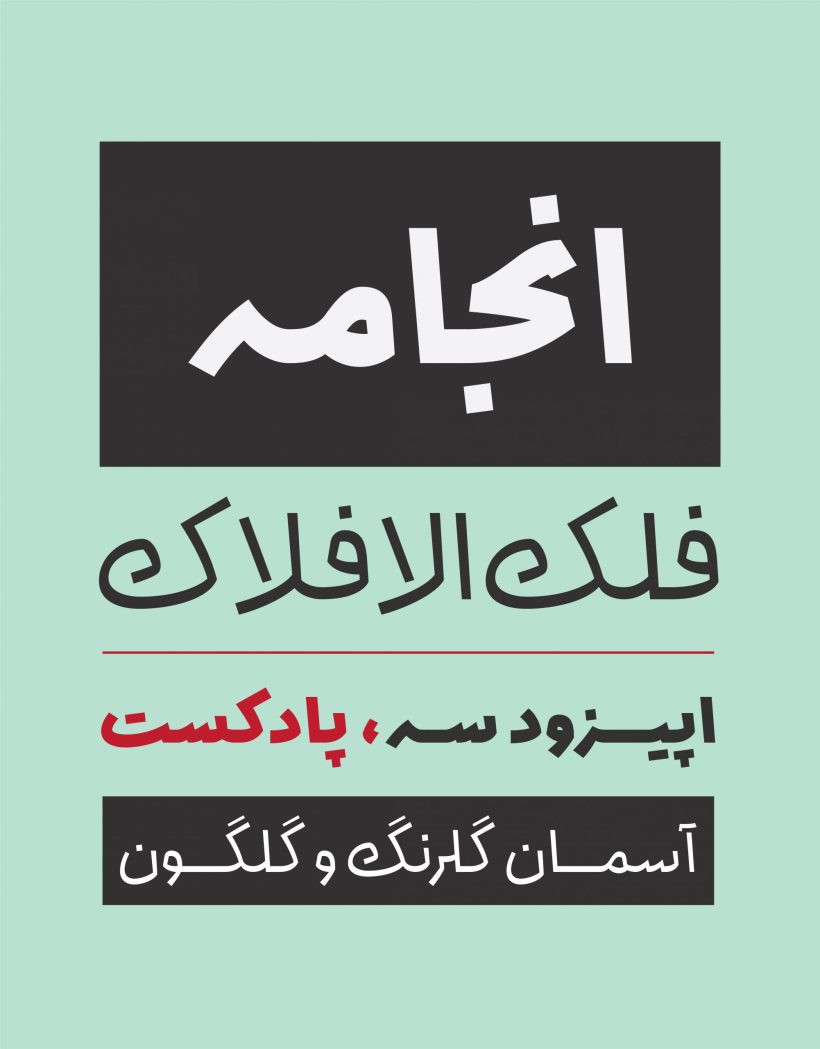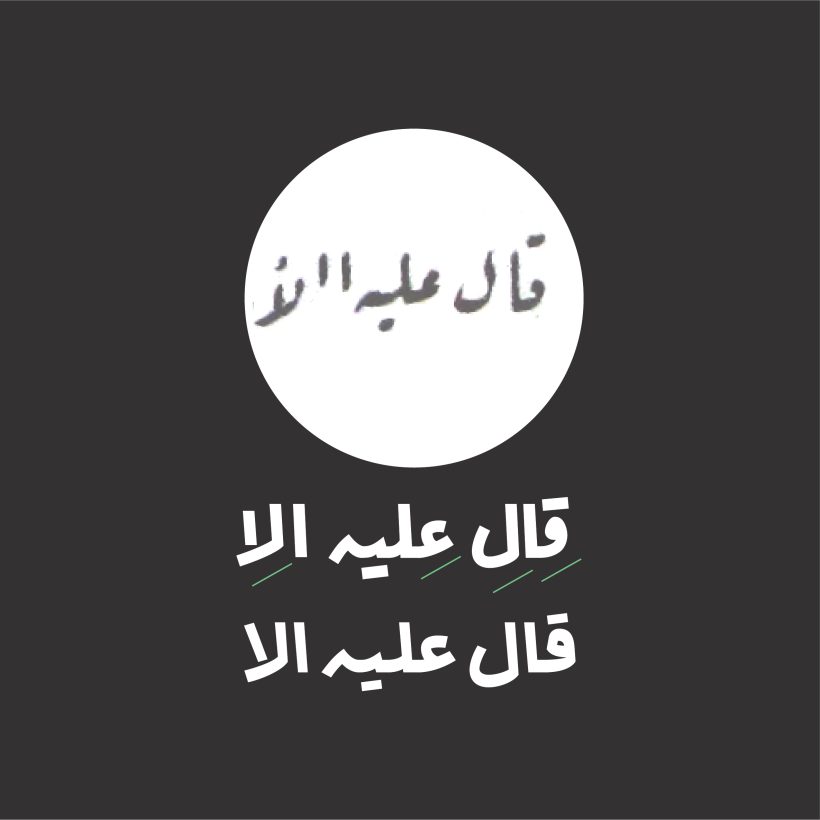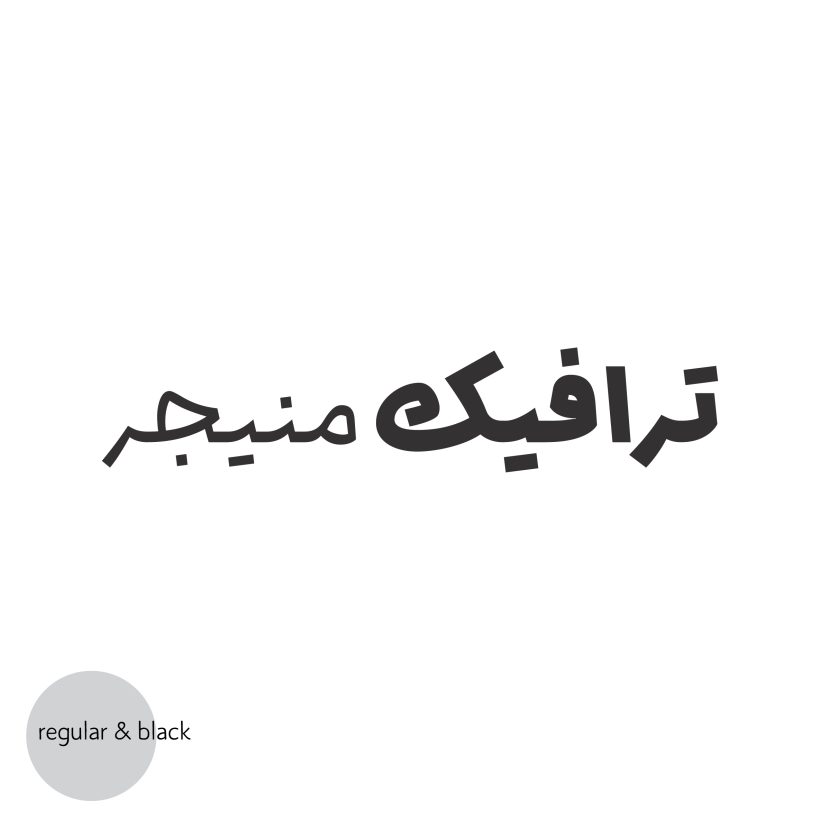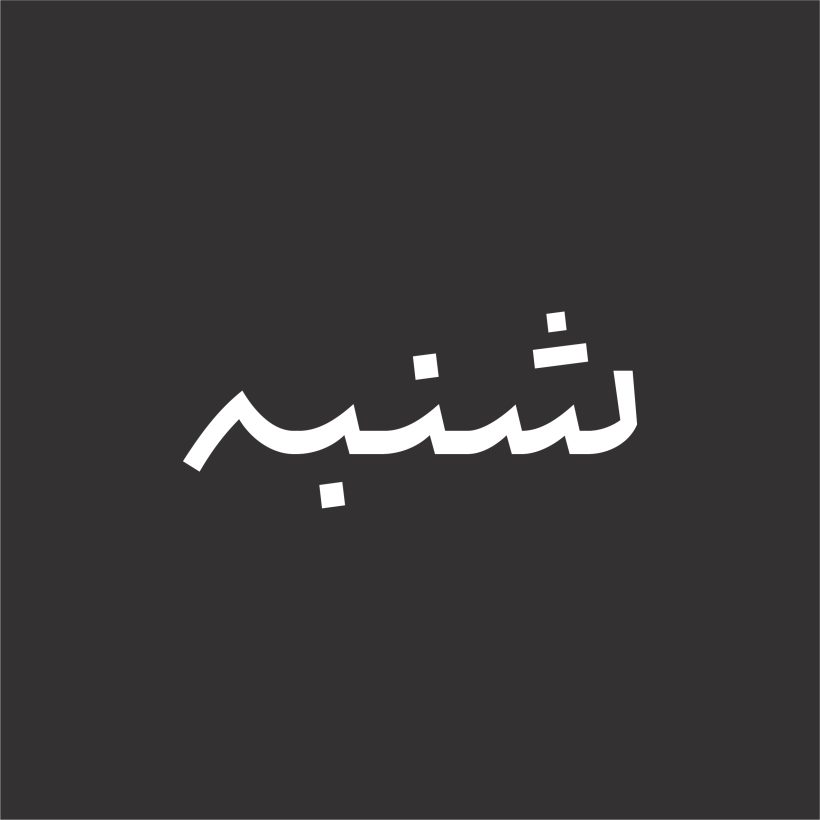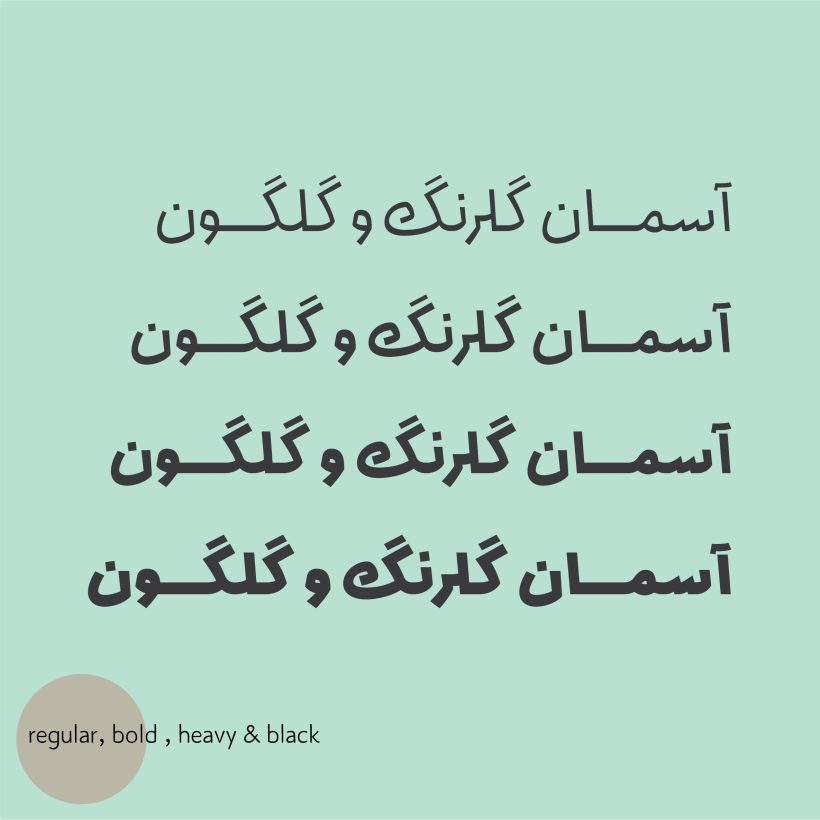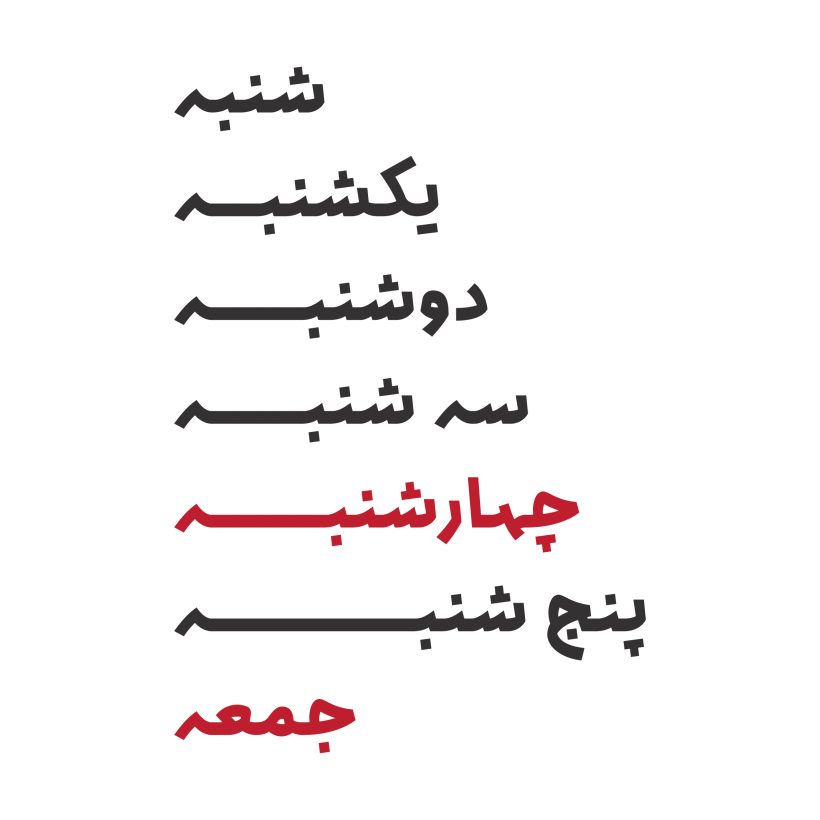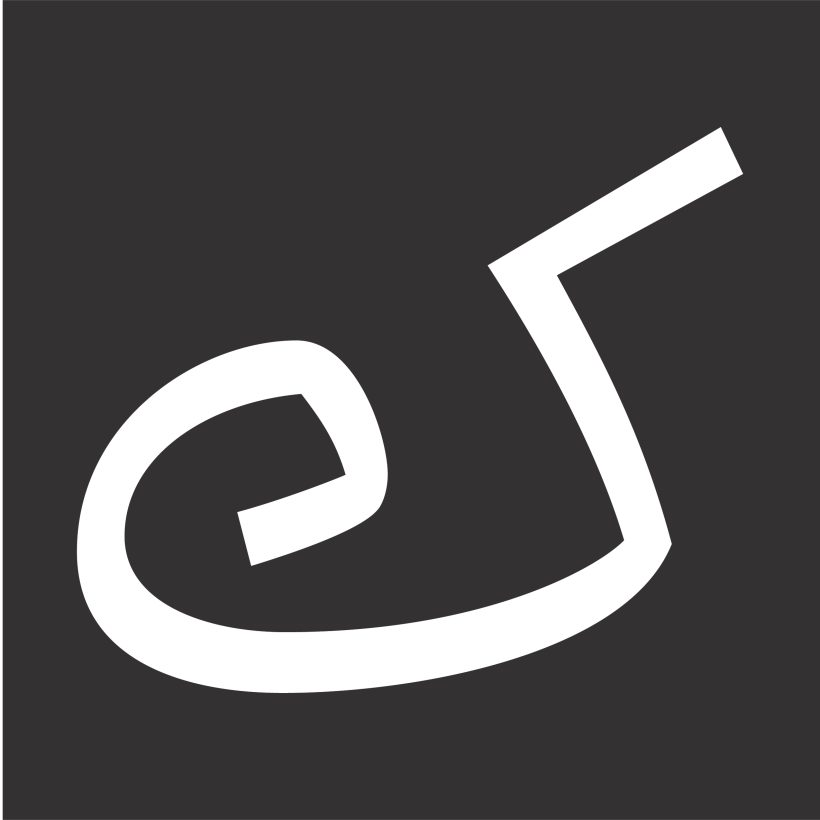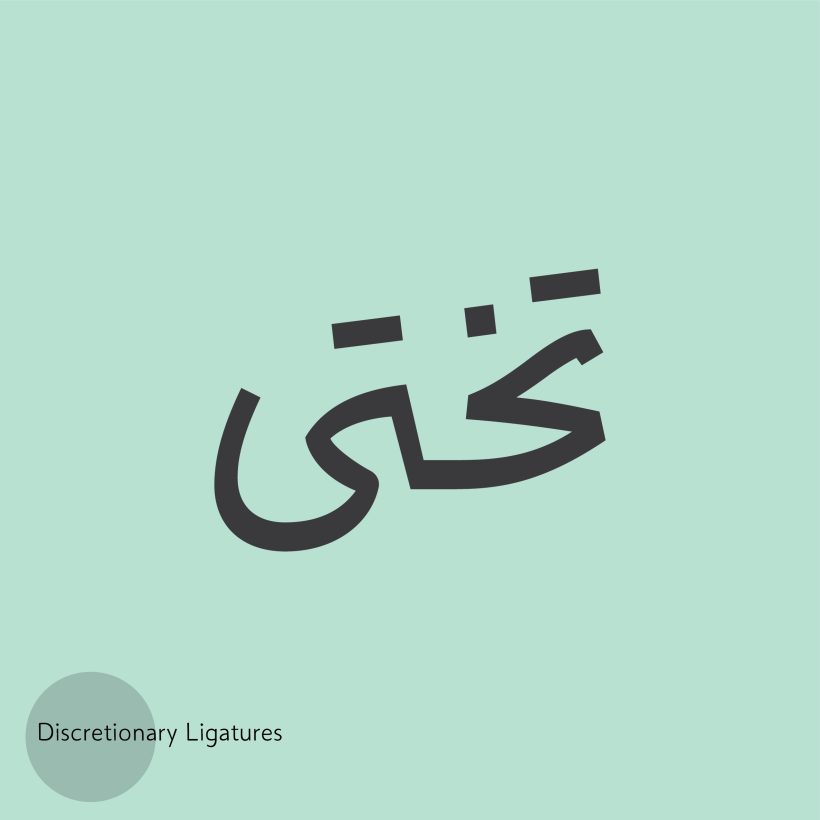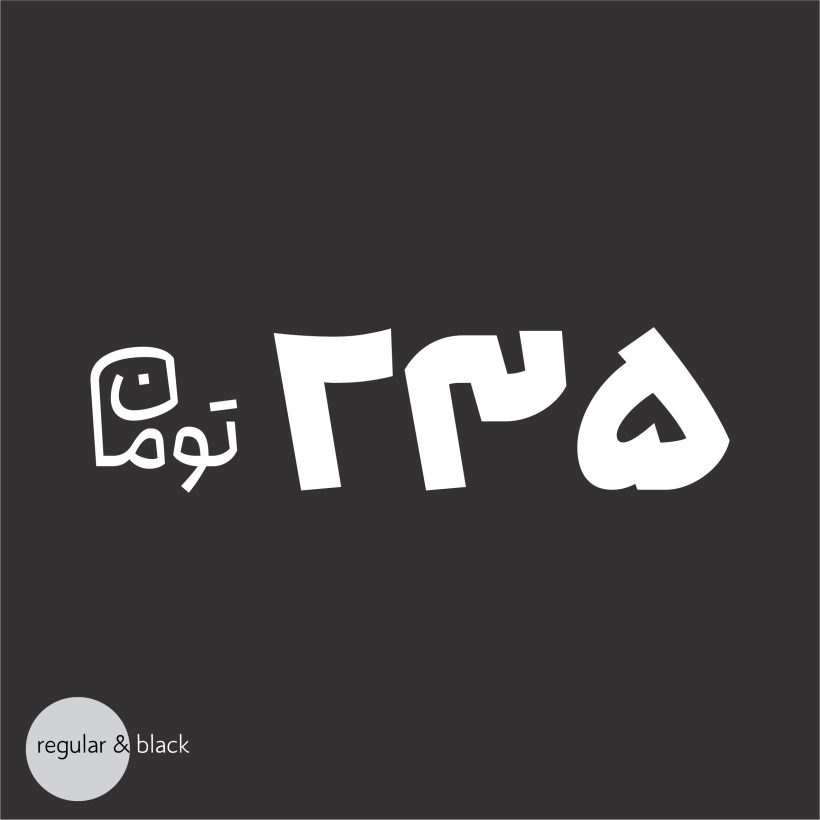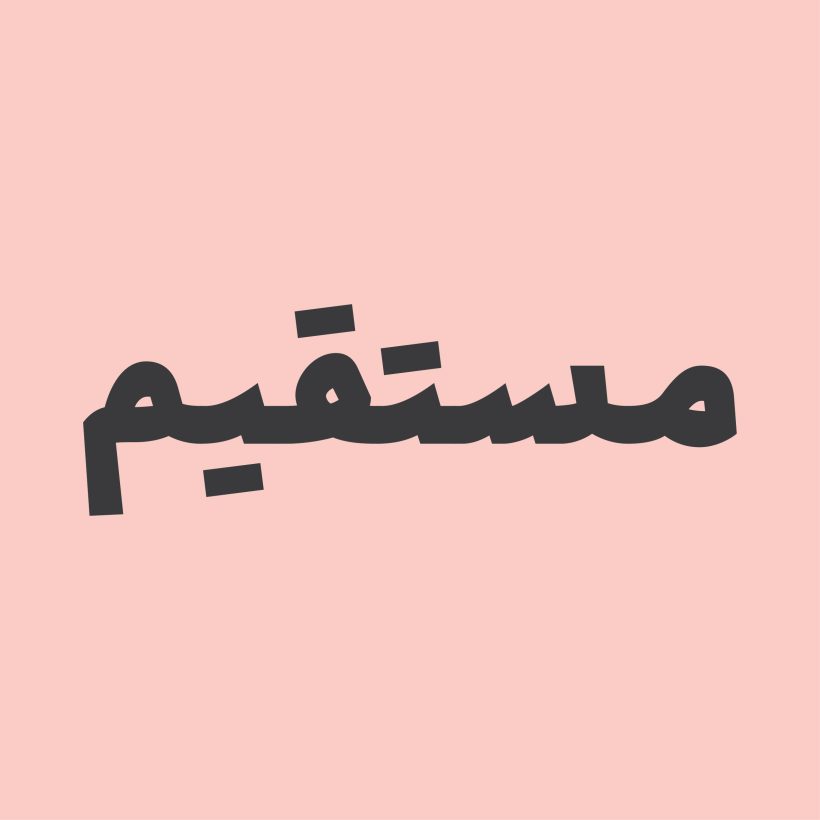
خانواده فونت انجامه
تایپ فیس انجامه تلفیقی از خطوط نسخ و رقعی ست. در طراحی این فونت پس از برداشــت اولیه از خط رقعی، برخی از ویژگیهــای خط نسخ برای خوانایی بیشتر حروف لحاظ شــــده است.
در فونت انجامه همانند خط رقعه، شاکله حرکتی برخی از حروف با حداقل گردش قلم و به شکل آسان نویسی طراحی شده است. الفات با شیب و بدون دور است و زاویه شروع و ختم حروف به شکل ساده است. حروف دندانه دار وسط چسبان همانند رقعه با کمترین حالت و گردش قلم طراحی شده است. دو نقطه ها و سه نقطه ها به شکل پیوسته است؛ خصوصیتی که ملهم از رقعه(به دلیل آسان نویسی و سرعت در کتابت) است.
در فونت انجامه، سعی شده همانند خط رقعی حرکات سطح بیشتری به کار رود. ضمناً استفاده از برخی کارکترها و لیگچرهای خط رقعی که کمتر در طراحی فونت مورد استفاده قرار گرفته و تلفیق آن با خط نسخ، لحنی جدید و عامیانه را تداعی می کند.
قواعد کرنینگ و اعراب گذاری ها در فونت انجامه اعمال شده است.
اعداد فارسی و عربی در فونت انجامه تنظیم شده و قابل استفاده است.
فونت انجامه با راهنمایی استاد صداقت جباری و توسط معصومه مصلح در سال 1402 طراحی شده است.